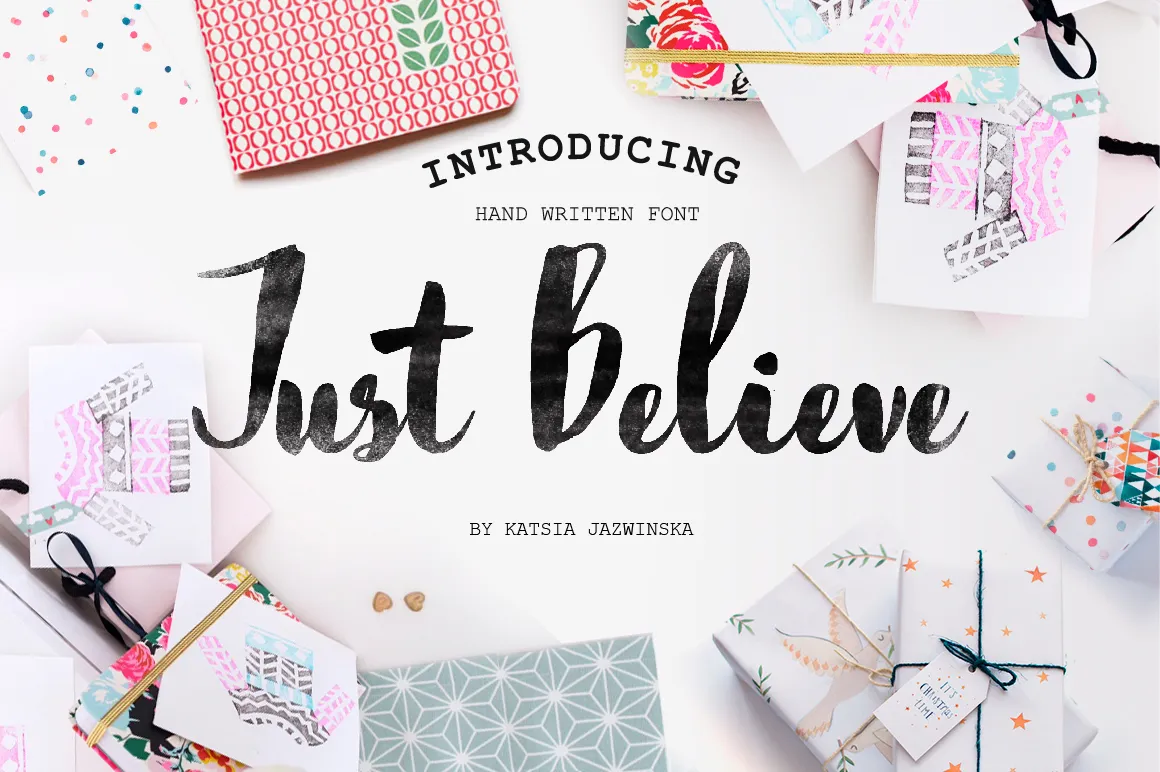
Just Believe Font – Fonte Grátis
Just Believe Font
A fonte “Just Believe” é uma criação artesanal projetada especialmente para aqueles que buscam uma fonte com uma aparência natural e elegante. Ela oferece letras maiúsculas e minúsculas, além de pontuação básica e números. Um destaque especial da fonte é seu aspecto brush stroke, que se assemelha a desenhos feitos à mão, dando um toque único e personalizado aos textos digitais. Hamilton, o designer desta fonte, abraçou essa ideia de arte digital ao criar “Just Believe”, apresentando uma opção em formatos .ttf e .otf para uso tanto no desktop quanto nos dispositivos móveis. Este é um recurso gráfico perfeito para aquelas criações que buscam transmitir uma sensação natural e moderna, mantendo a elegância do estilo brush strokes que sempre fazem sucesso entre os designers de fontes contemporâneos.